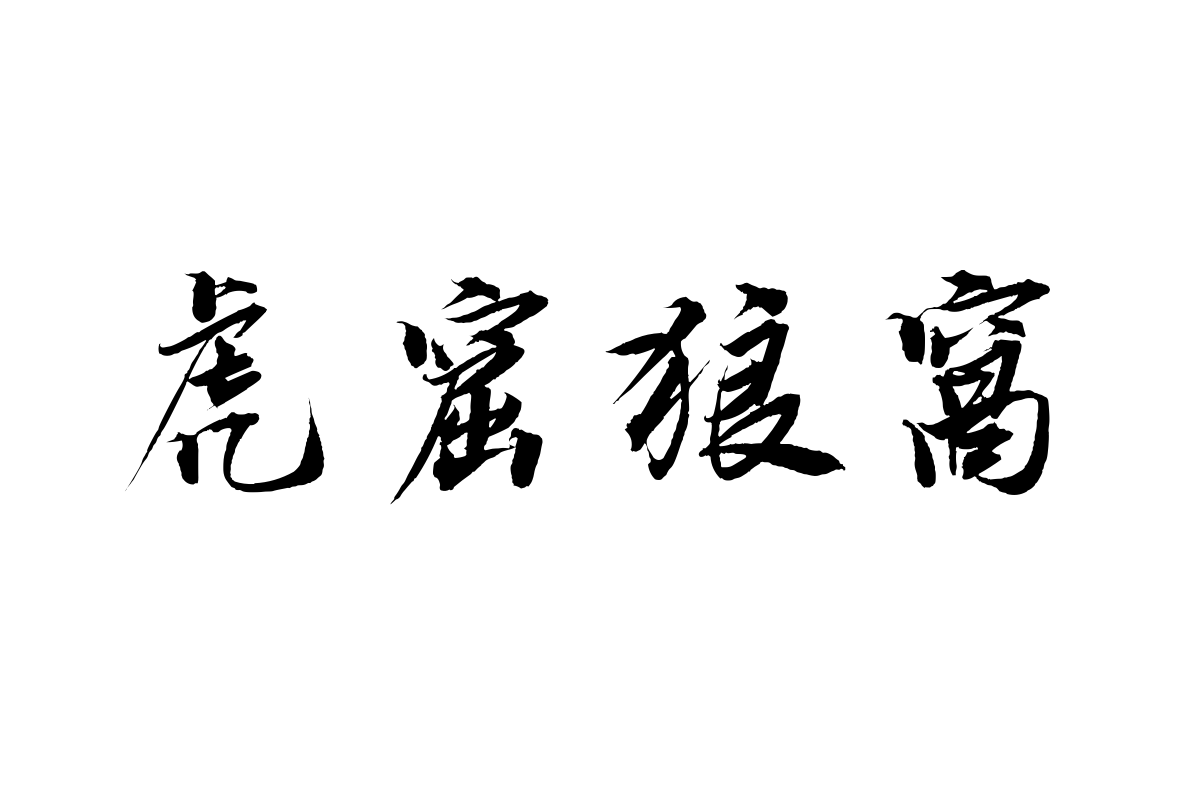
汉仪黄科行书繁字体是一款具有现代感的行书字体,它的特点是笔画流畅、结构紧凑。这款字体适用于多种场景,如标题、正文、广告等。它的设计灵感来源于古代书法艺术,但又融入了现代审美元素,使得这款字体既有古典韵味又不失时尚感。
汉仪黄科行书繁字体的笔画粗细适中,既不会过于粗犷也不会过于细腻,给人一种舒适的感觉。同时,这款字体的字形结构也较为规整,没有过多的装饰性线条,这使得它在视觉上更加简洁明了。